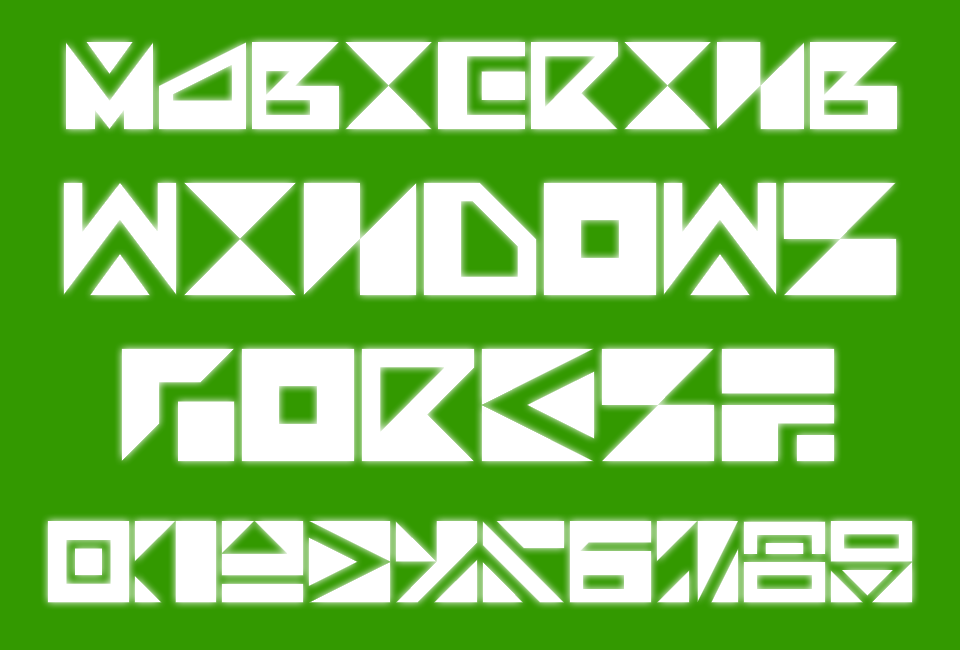
『魔法少女育成計画』のアニメ版に登場する魔法陣フォント「MagicRing」
一風変わった能力を操る魔法少女たちの世界観にマッチする幾何学デザイン
「MagicRing」は“まほいく”こと、ライトノベル『魔法少女育成計画』のアニメ版プロモーションビデオに採用されたと思われるフォント。大文字のアルファベット、数字のほか、一部の記号も収録している。
『魔法少女育成計画』は、ソーシャルゲームを発端とする魔法少女同士の死闘を描いた作品。アニメ版が今秋10月からTOKYO MXやBS11などで放送される予定であり、公式サイトでは16人の魔法少女キャラと声優が4回に分けてプロモーションビデオで発表された。
その映像内の演出として登場するフォントを目視で確認したところ、窓の杜ライブラリにも収録されている「MagicRing」の可能性が高い。魔法陣の紋様をテーマとした同フォントは『魔法少女育成計画』に打ってつけなため、気付いたファンも多いだろうか。
“困っている人の心の声が聞こえるよ”“目の前の相手になんでも命令できるよ”など、一風変わった能力を操る魔法少女たちの世界観にも「MagicRing」は見事にハマっている。現段階では本編に使われるとは限らないものの、無料フォントの意図がそのまま具現化された珍しい例かもしれない。